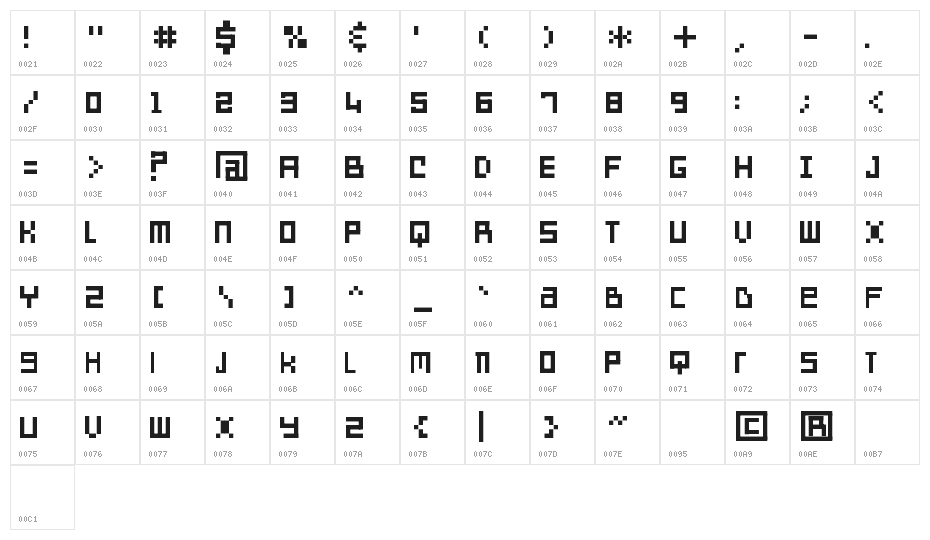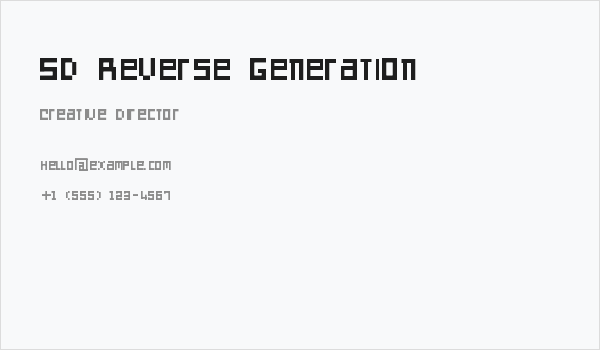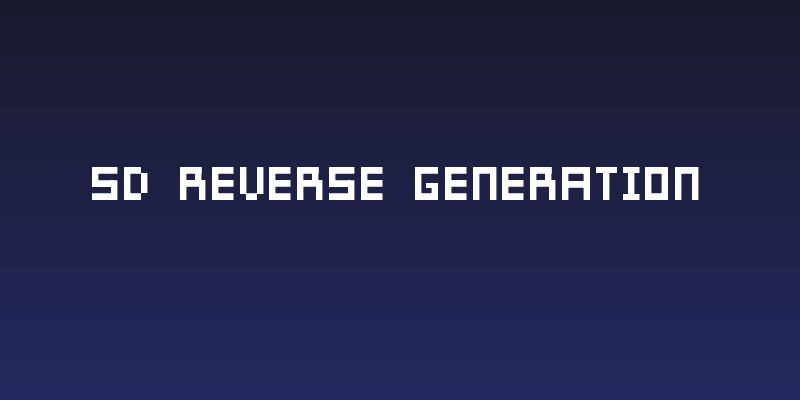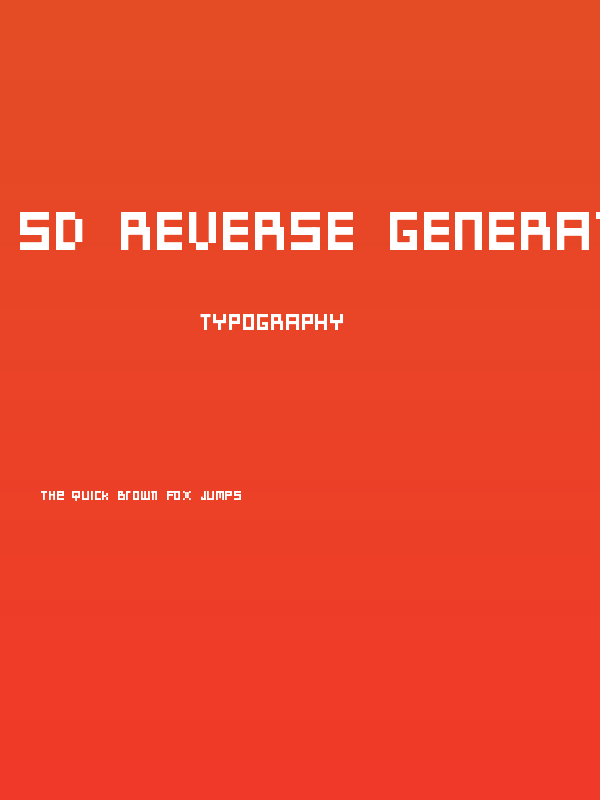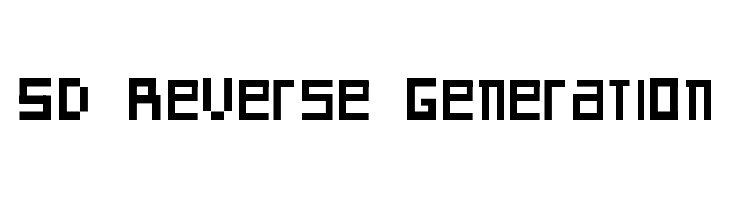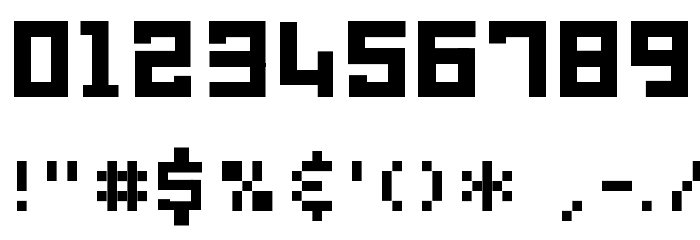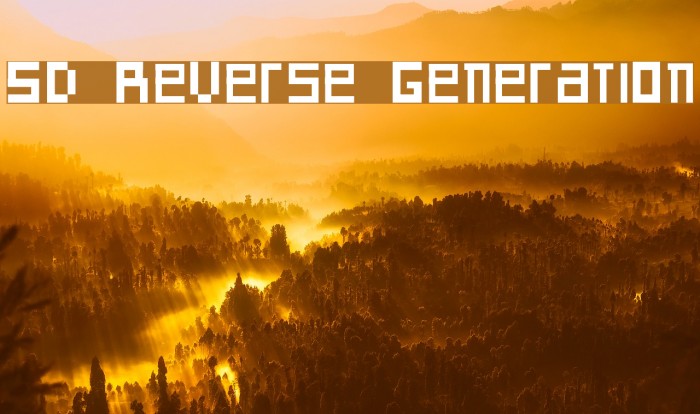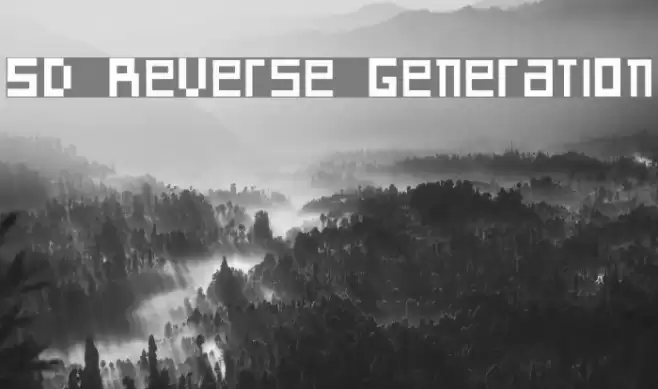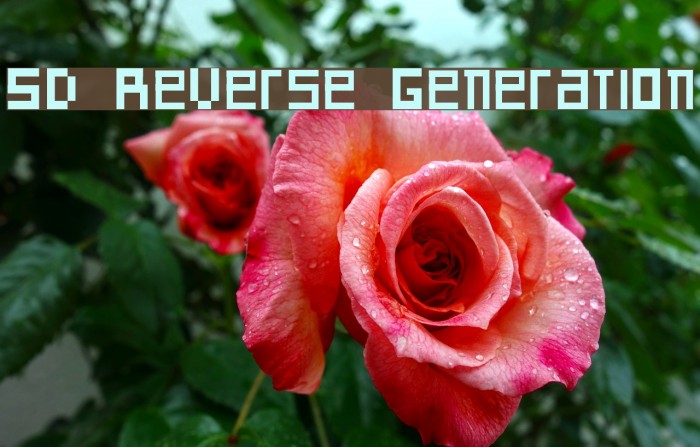
SD Reverse Generation Font
Justin Callaghan
| 全体的なスタイル | Retro, Digital |
| 用途 | Headlines, Logos, Digital Art |
| おすすめプロジェクト | Ideal for video game graphics, tech-themed posters, retro designs, and digital art projects. |